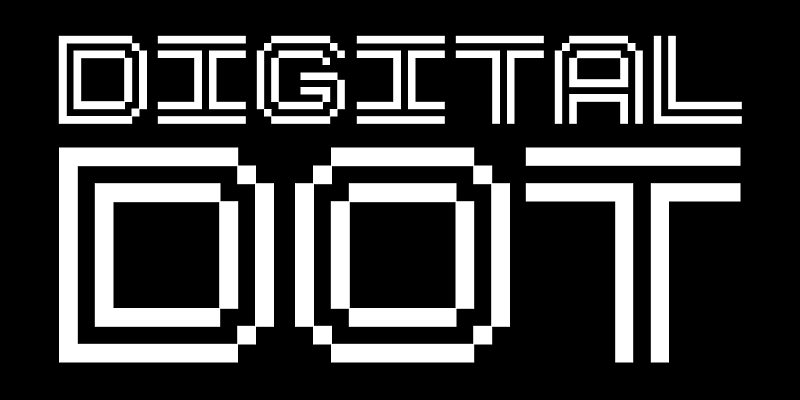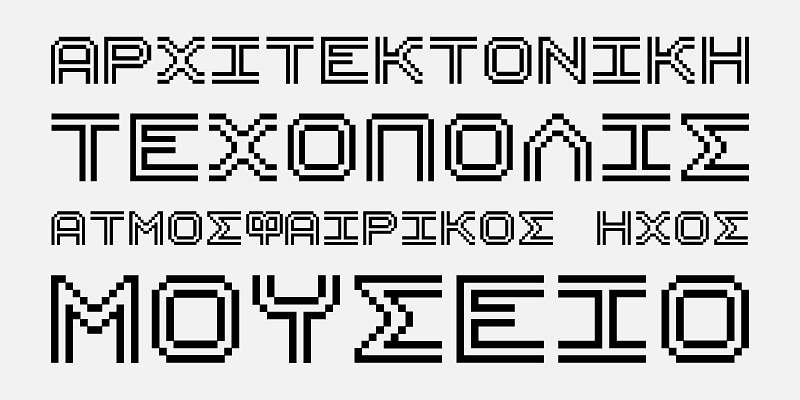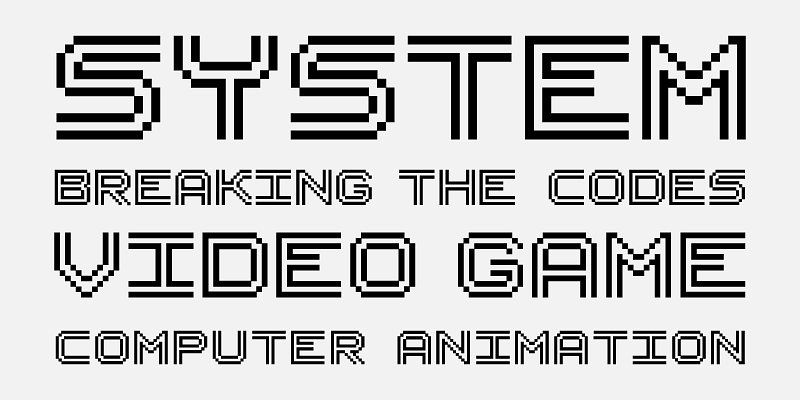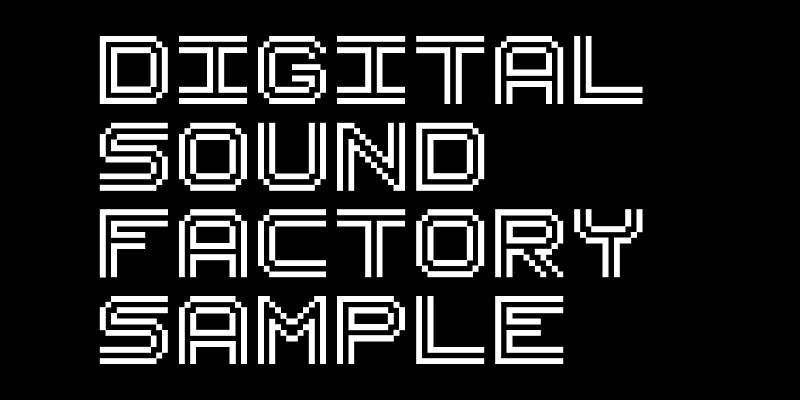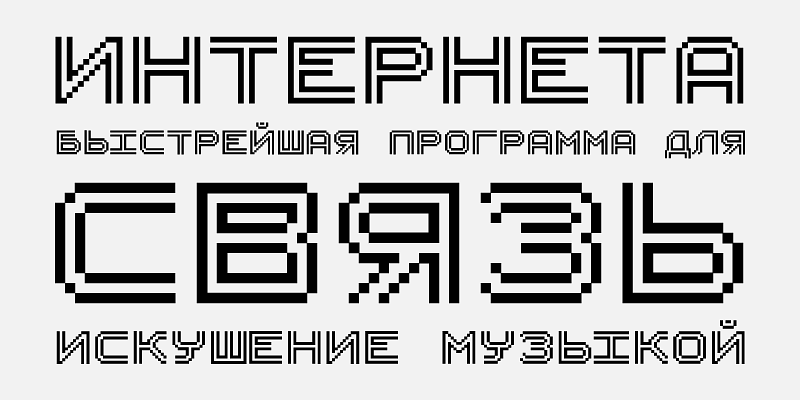
A PF Uniform é uma fonte de pixel monoespaçada bastante distinta que se destaca em títulos. Ela foi originalmente criada para uso online, mas também fica ótima em conteúdo impresso. Ao variar o espaçamento, as telas geradas ficam bem interessantes. Esta versão inclui latim, grego e cirílico. Você também pode usá-la no Photoshop para criar arquivos GIF, principalmente títulos e botões, para páginas online.